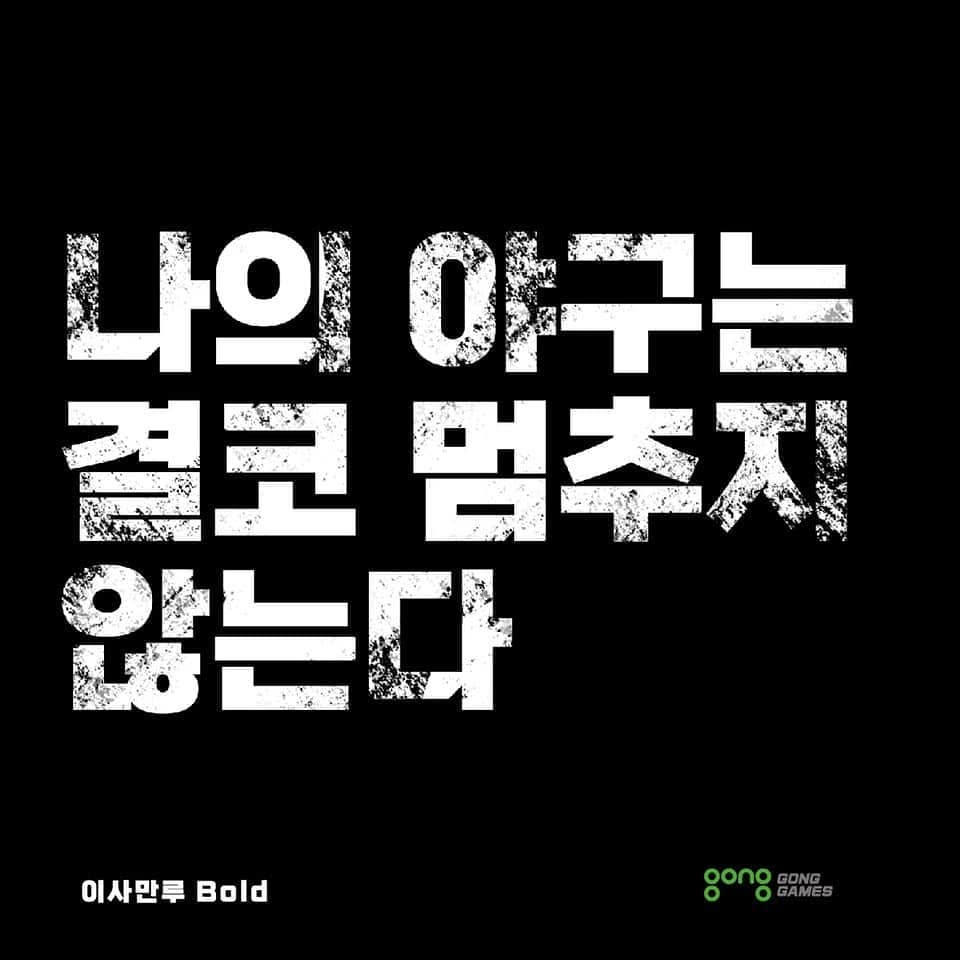
이사만루체 — 추천 용도
이사만루체 — 공게임즈 X 폰트릭스에서 배포하는 무료 폰트입니다. 각진 자소와 단단한 네모틀에 역동적인 변형을 더한 힘 있는 고딕체
야구 게임을 만드는 공게임즈가 폰트릭스와 함께 만들어 2020년 한글날에 배포한 서체입니다.
고딕 계열인데 획이 맞닿는 부분에 꺾인 처리를 포인트처럼 넣은 것이 특징입니다. 그 각진 마감이 스포츠 중계 자막 같은 인상을 냅니다.
굵기는 Light와 Medium, Bold 세 가지입니다. 게임 서체 가운데 드물게 본문에도 쓸 수 있는 구성이라, 제목은 Bold로 본문은 Light나 Medium으로 나눠 쓰라고 안내되기도 합니다. 스포츠나 게임 관련 콘텐츠, 강한 제목에 어울립니다. 무료로 상업적으로 쓸 수 있지만 임의로 수정해 유료로 파는 것은 금지됩니다.